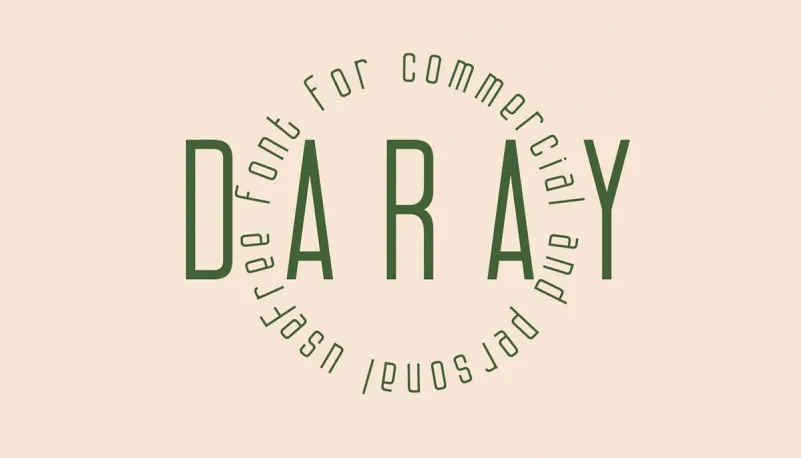
Daray Font – Fonte Grátis
Daray Font
Esta é uma fonte sans-serif simples e minimalista criada pelo designer Maxim Raikov. A simplicidade é a chave para o sucesso. Duas formas de linhas retas e curvas suaves se encontram – Daray. Esta fonte tem suporte multilíngue, incluindo inglês e russo. Composta em um estilo sans-serif, ela oferece uma ótima experiência visual tanto em projetos pessoais quanto corporativos. Se você está procurando por uma fonte moderna que se destaca pelo equilíbrio entre simplicidade e eficiência, Daray pode ser o seu novo favorito.